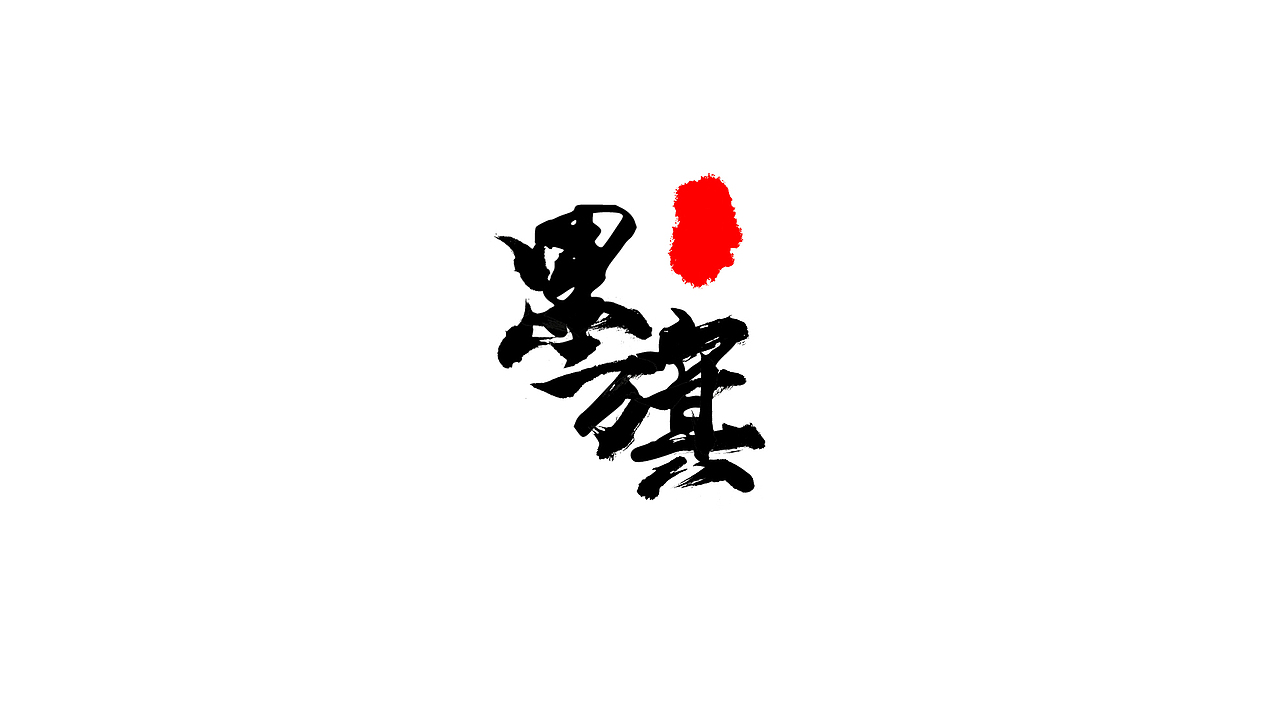
墨旗APP标志字体设计
墨旗APP是一款展示旗袍文化的文创软件,拥有在线设计师预约功能。我为其设计了标志,采用毛笔字 的手法,将墨旗两个字巧妙且生动的结合在一起,洒脱的字形予以墨旗以生命力和创新力,做完之后心情大为舒畅。此款字体也是自己在沉淀许久之后的感悟之作,虽显粗糙,聊表对设计的追求与坚持,始终以匠人之姿态,每天改变一点。每天做一点,让这个世界变得更好。
墨旗APP标志字体设计